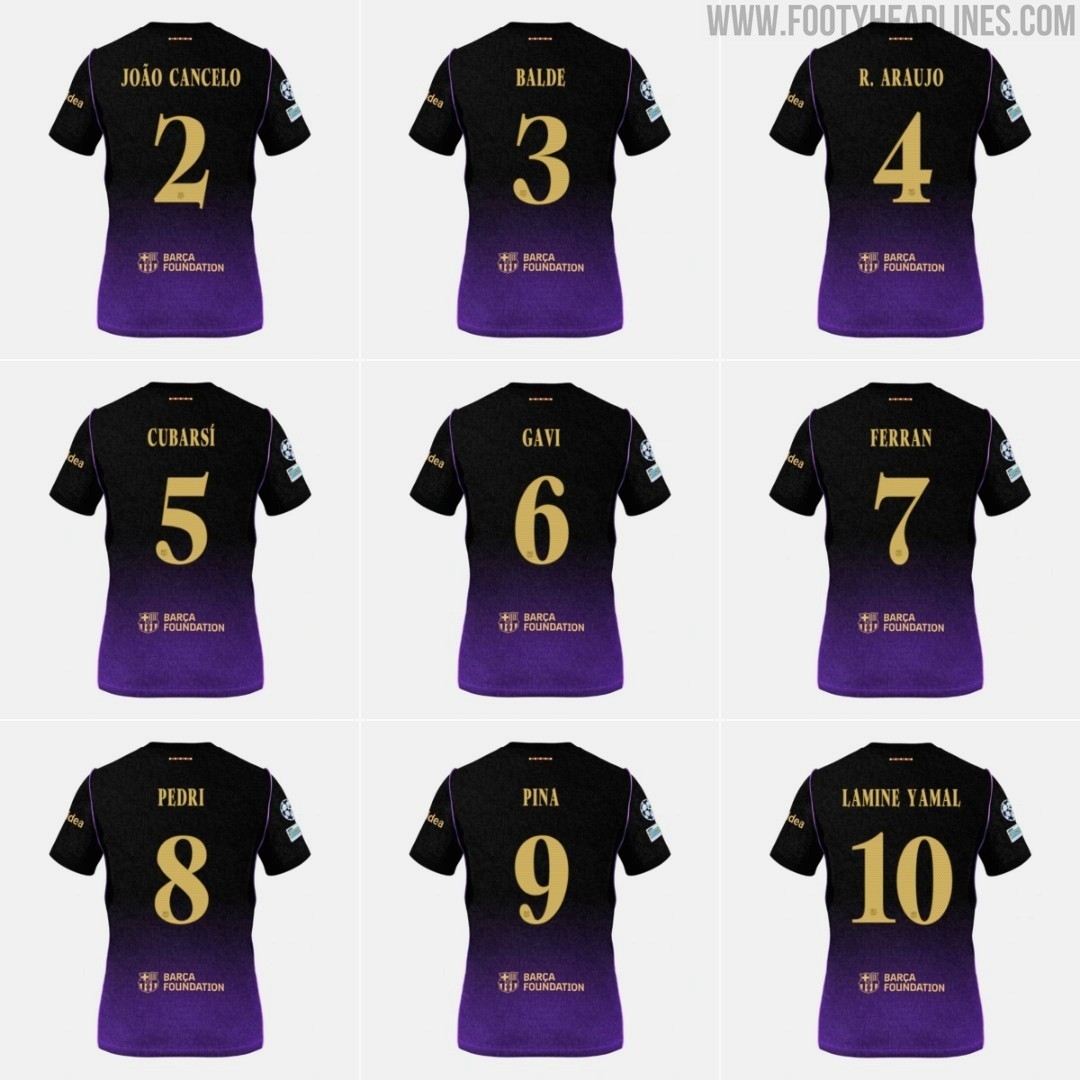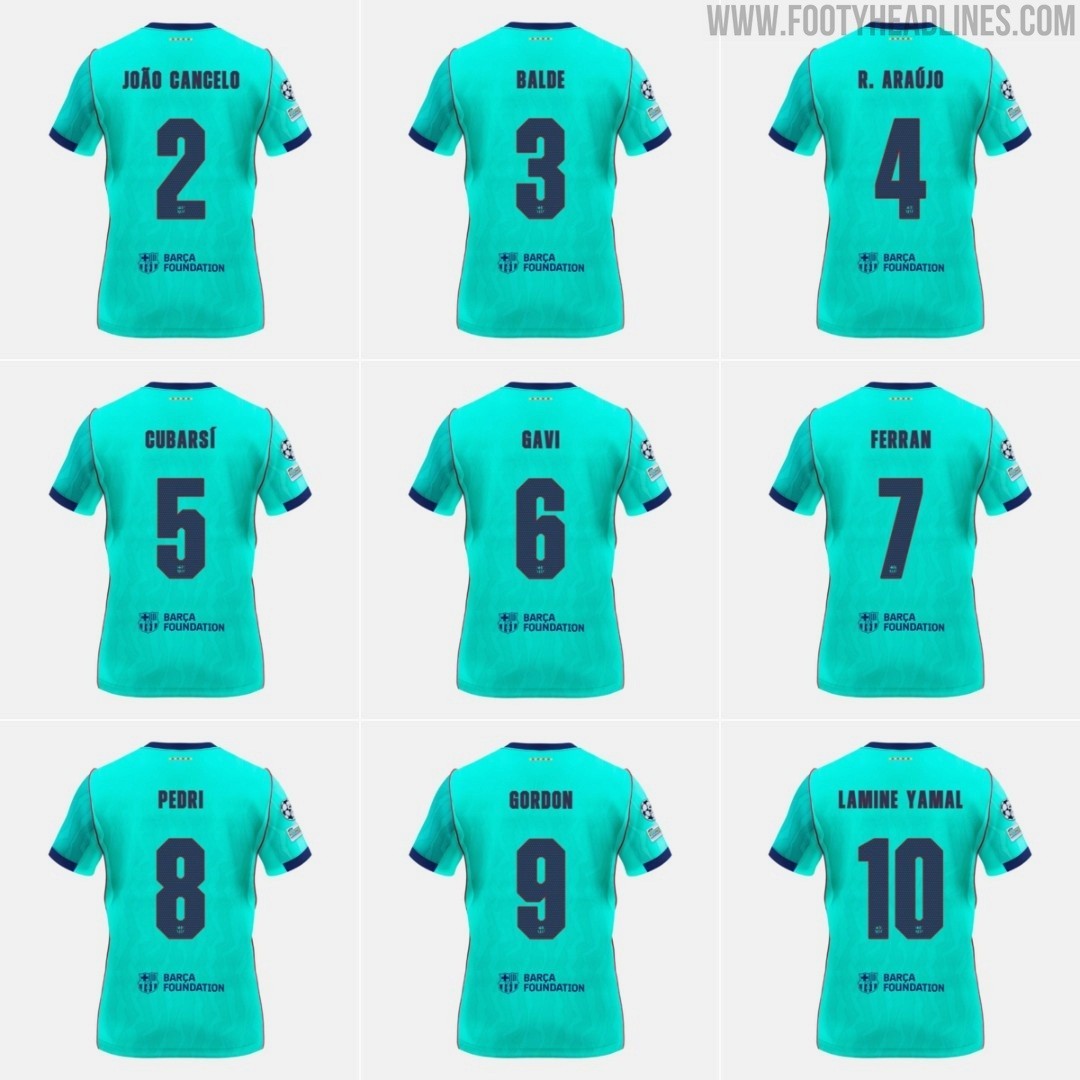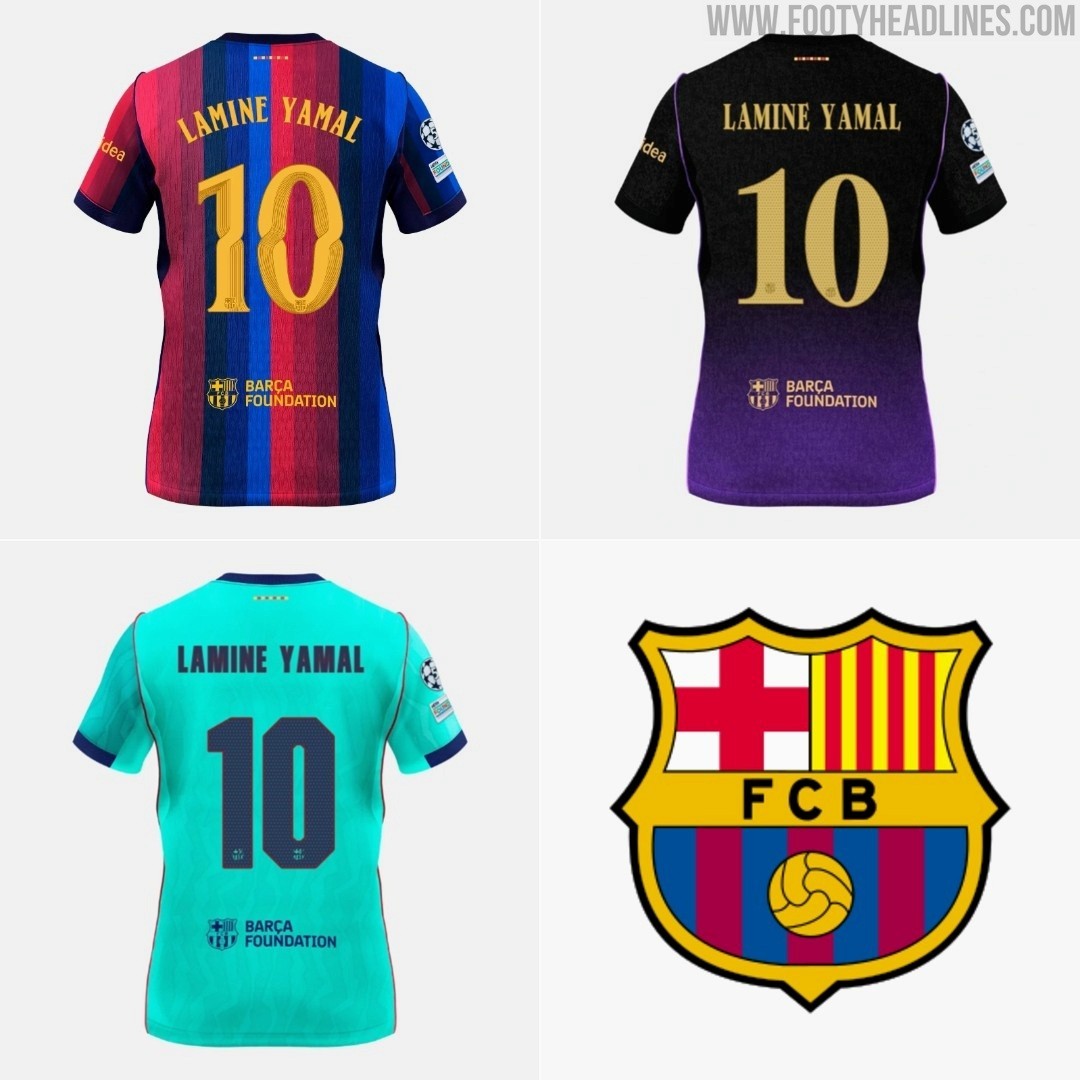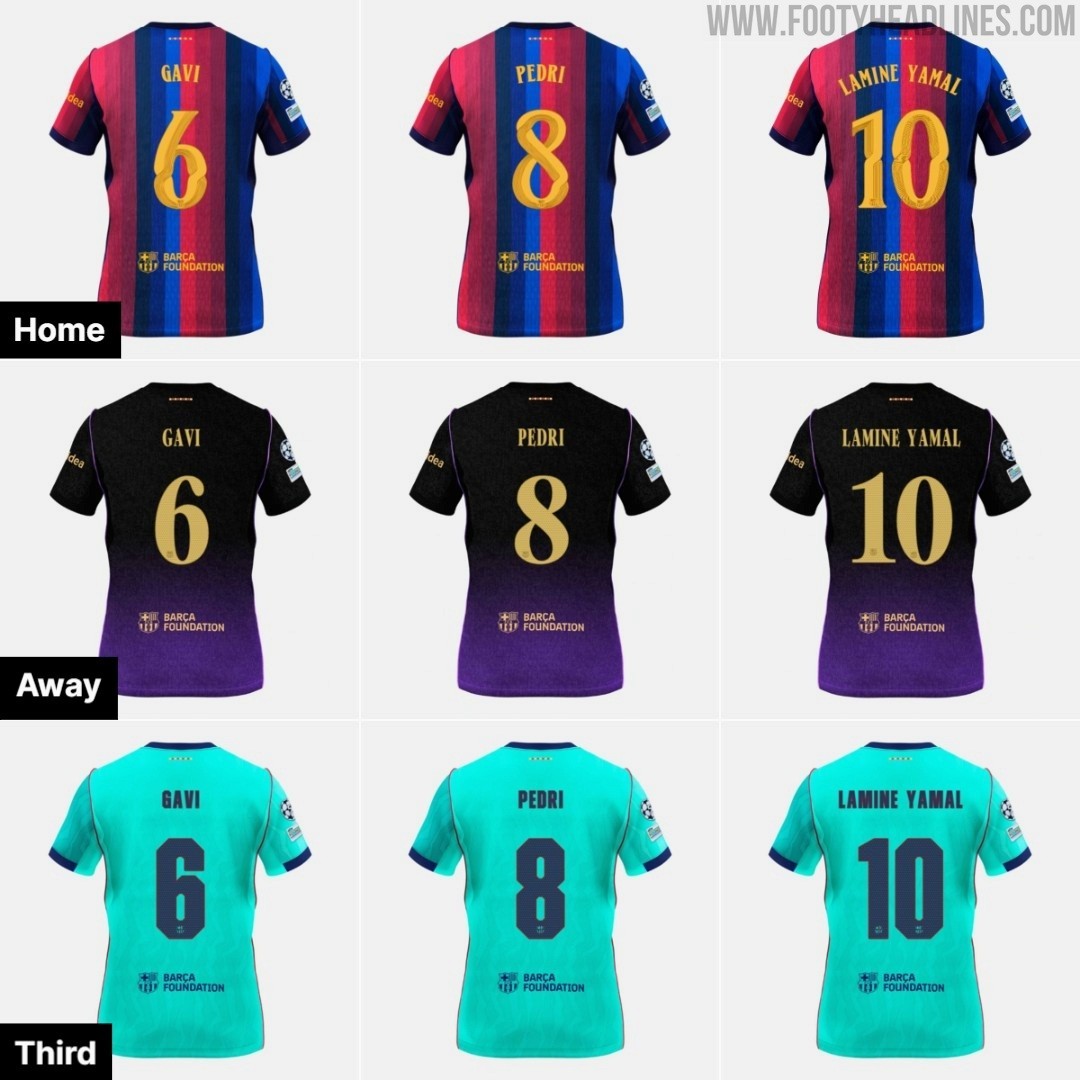
Drei maßgeschneiderte Schriftarten für die Heimtrikots, Auswärtstrikots und das dritte Trikot des FC Barcelona 26–27 veröffentlicht
• Neue Schriftarten für die Saison 26/27: Der FC Barcelona hat nach sieben Saisons mit demselben Schriftbild drei brandneue, maßgeschneiderte Schriftarten für seine Heim-, Auswärts- und dritten Trikots der Saison 2026/27 veröffentlicht.
• Design-Unterschiede der Schriftarten: Während die Schriftarten für das Heim- und Auswärtstrikot weiche, fließende Formen mit eleganten Kurven aufweisen, inspiriert vom katalanischen Modernismus, ist die Schriftart für das dritte Trikot kantiger und eckiger gestaltet.
• Besonderheit des Auswärtstrikot-Schriftzugs: Die Schriftart des Auswärtstrikots 26/27 präsentiert sich in einem satten, metallischen Goldton, der einen starken Kontrast zum dunkel-schwarz-lila Hintergrund bildet und perfekt zu anderen goldenen Elementen des Trikots passt.
Nachdem der FC Barcelona sieben Saisons in Folge denselben Schriftensatz verwendet hatte, hat der Verein nun eine beeindruckende Veränderung vollzogen und drei brandneue, maßgeschneiderte Schriftarten vorgestellt, die jeweils speziell für das Trikot, das Auswärtstrikot und das dritte Trikot der Saison 2026/27 entworfen wurden.
FC Barcelona 26/27-Trikot-Schriftarten – 3 Editionen
Drei maßgeschneiderte Schriftarten für die Heimtrikots, Auswärtstrikots und das dritte Trikot des FC Barcelona 26–27 veröffentlicht
Die neuen FC Barcelona 26–27 Trikot-Schriftarten gibt es in drei unterschiedlichen Versionen, die speziell auf jedes Trikot zugeschnitten sind. Während die Schriftarten für das Trikot und das Auswärtstrikot eine weiche, fließende Eigenschaft mit eleganten Kurven aufweisen, ist die Schriftart für das dritte Trikot eher kantig und eckig gestaltet.
Die neue Schriftart für das FC Barcelona Trikot 26–27 bricht komplett mit der üblichen, kantigen Sporttypografie und führt künstlerische Linien ein, die stark von der berühmten Bewegung „Modernisme Català“ (katalanische Modernismus-Architektur) inspiriert sind.
Schriftart des FC Barcelona Auswärtstrikots 26–27
Die neue Schriftart des FC Barcelona Auswärtstrikots 26-27 präsentiert sich in einem satten, metallischen Goldton. Dieser leuchtende Goldfarbton bildet einen starken Kontrast zum dunklen schwarz-lila Hintergrund des Trikots und passt perfekt zu den goldenen Ärmelborten, den Sponsorenlogos und dem Vereinswappen auf der Vorderseite.
Schriftart für das dritte Trikot des FC Barcelona 26–27
Die neue Schriftart für das dritte FC Barcelona Trikot 26-27 besticht durch eine ausgesprochen moderne, strukturierte Ästhetik, die sie vom Rest der Vereinskollektion 2026–2027 abhebt.